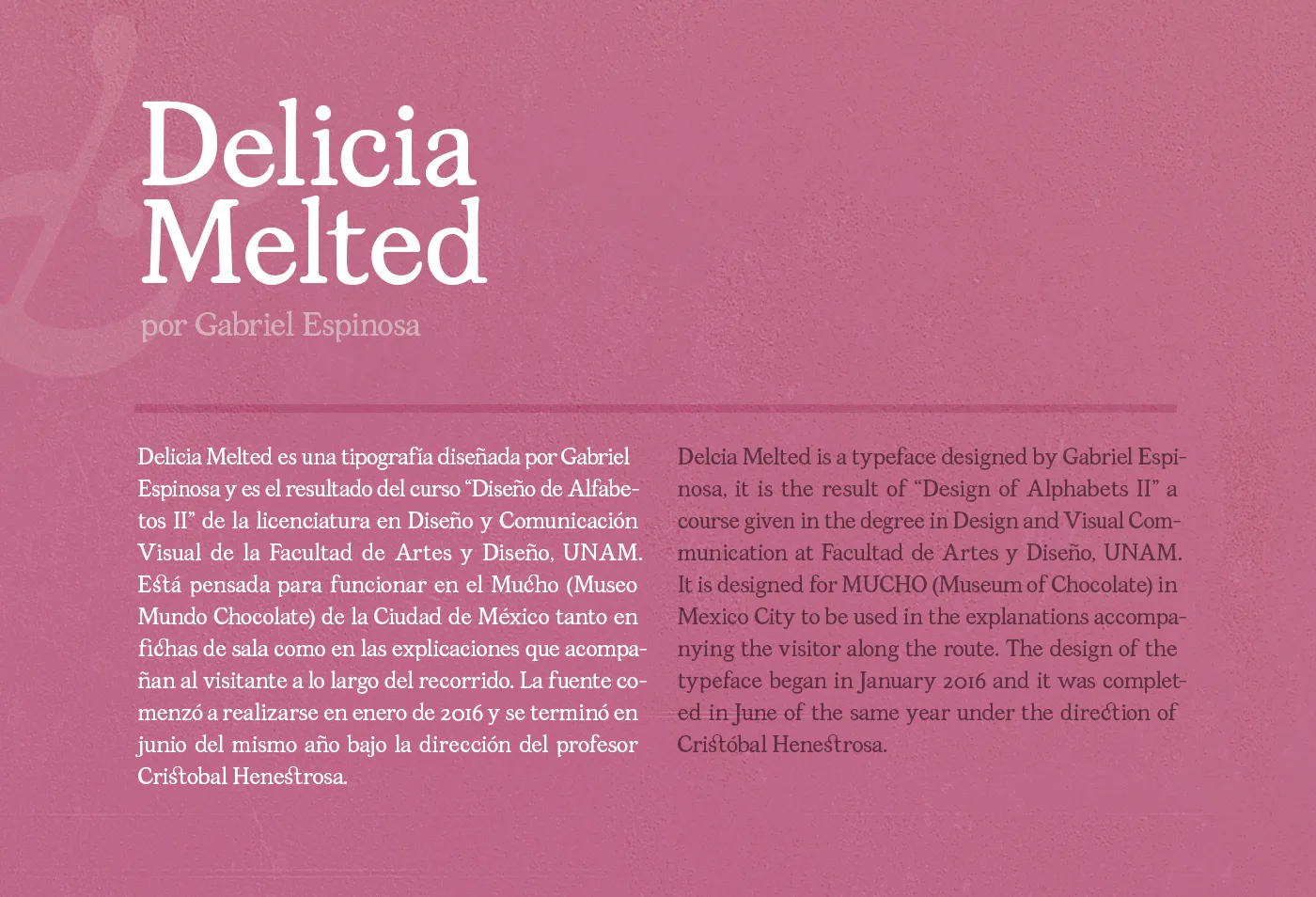
Delicia Melted é uma tipografia elaborada por Gabriel Espínova, resultado do curso “Design of Alphabets II” oferecido na graduação em Design e Comunicação Visual na Facultad de Artes y Diseño, UNAM. Este projeto criativo resultou numa fonte elegante e única, com detalhes que tornam a experiência de escrita mais agradável. Com sua tipografia serif, Delicia Melted é perfeita para projetos que precisam de uma aparência sofisticada e profissional. É especialmente adequada para títulos e seções principais dos documentos, como resenhas de livros ou artigos acadêmicos importantes. Além disso, a fonte traz um toque delicado e refinado que torna qualquer projeto mais encantador. Delicia Melted é uma escolha perfeita para quem busca encontrar uma maneira única de expressar sua visão gráfica, mantendo-se fiel às origens serif. Com seu design cuidadosamente elaborado, a fonte Delicia Melted oferece aos profissionais e amadores um recurso que trará brilho à qualquer projeto, seja ele para impressão ou digital.